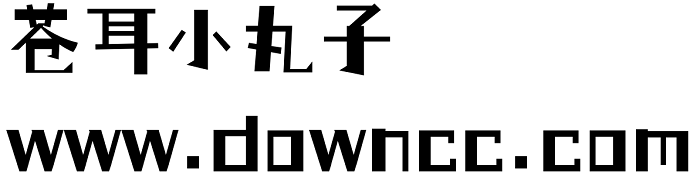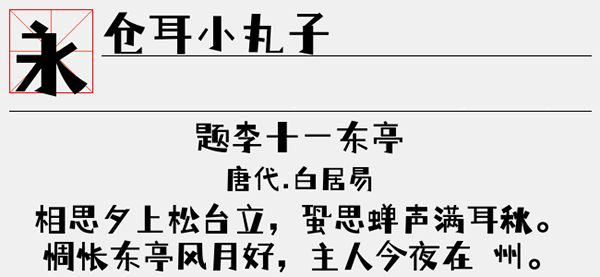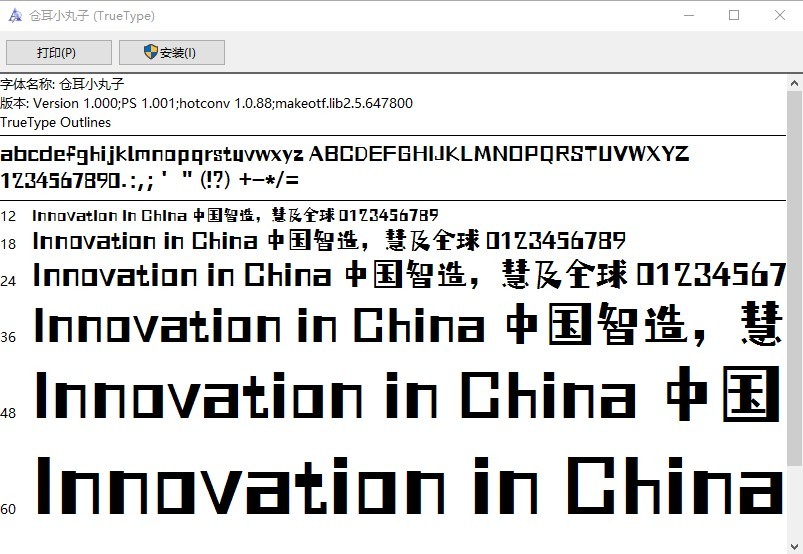
倉耳小丸子字體免費(fèi)版是可以運(yùn)用到不同場合的藝術(shù)性字體,字形俏皮可愛,天真爛漫,筆畫錯落有致,看起來極具個性特點(diǎn),對比夸張,吸引不少用戶喜歡,尤其適合在海報設(shè)計、包裝設(shè)計、平面設(shè)計等領(lǐng)域使用,好用又方便!
倉耳小丸子字體字庫是一款讓人賞心悅目、百看不厭的中文字體,適合各類廣告和產(chǎn)品包裝設(shè)計應(yīng)用。
1、搞怪的字型結(jié)構(gòu)和出乎意料的空間調(diào)整讓字體多了幾分調(diào)皮可愛之氣
2、倉耳小丸子結(jié)構(gòu)靈活,選用粗細(xì)對比夸張的筆畫,使字體更具視覺沖擊力
3、筆畫錯落有致,打破了許多固有的排列模式,這款字在寬松的氛圍中營造出天真爛漫的感受